Bar La Blanquita
Cuando me preguntan por que este proyecto, uno de los pilares es personal, de mi Familia. En los años 50 mis abuelos María Cuétara y Julio Garaña, provenientes de Asturias, abrieron un pequeño Bar en la Cuesta de la Atalaya. Se llamaba «La Blanquita». En el durante más de 2 décadas se fueron haciendo conocidos por sus famosos «Mejillones en Salsa»; literalmente era Kilos los que se vendían cada semana, en especial los Fines de Semana, donde mi madre me cuenta siempre que mi abuela no salía de la cocina porque no daban a basto.  Mi Abuelo se fue ganando prestigio en el sector hostelero y decidieron traspasar el Bar. Él siguió vinculado a la hostelería como Jefe de Cuadrilla de Camareros extras, siendo un referente y donde estuvo en activo más allá de su jubilación y además fue quien me enseñó el oficio de Camarero, donde estuve más de 20 años trabajando.
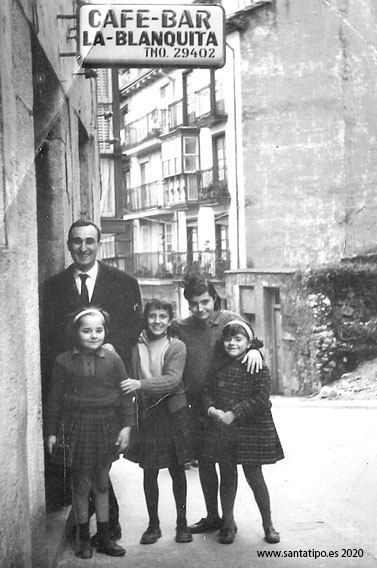
Rótulo principal (Año 57) / Foto: Archivo familiar
María y Julio. Años 50 / Foto: Archivo Familiar
Los Parroquianos, quienes dan vida a los bares. Finales de los 50. / Foto: Archivo Familiar
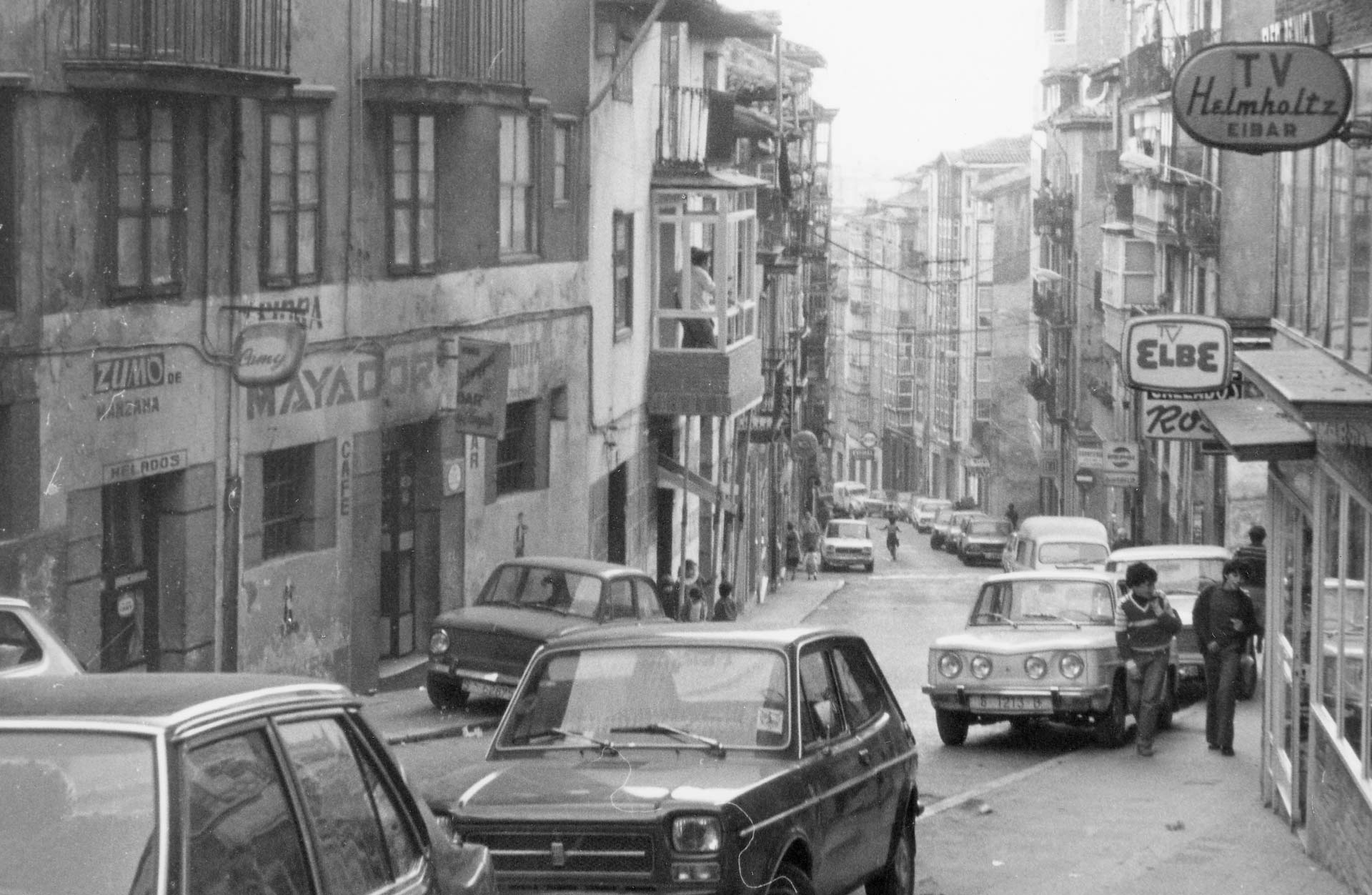
Desde los 70s la fachada ya contaba con rotulación publicitaria de Sidra Mayador, así como el cambio de los rótulos, siendo sustituido por uno patrocinado y el añadido de Camy junto a la puerta de venta de Helados. Vista parcial de la calle Cuesta de la Atalaya, en Santander, 1980. Autor Desconocido. Colección Archivo Fotográfico Histórico Municipal. Centro de Documentación de la Imagen de Santander, CDIS, Ayuntamiento de Santander. // www.santatipo.es //
Hoy todo ello ha desaparecido, así como todo el paisaje visual que se apreciaba. Foto: Google Maps (Septiembre, 2019)
Es cierto que a veces estas historias quedan en la familia, pero cuando lo hablas con gente de la calle o del barrio, rápidamente se acuerdan y te cuentan como ellos lo veían y lo vivían. Y ese es el motivo, sacar a la luz esa memoria, que a través de sus rótulos podemos rescatar y preservar, y en este caso reproducir.